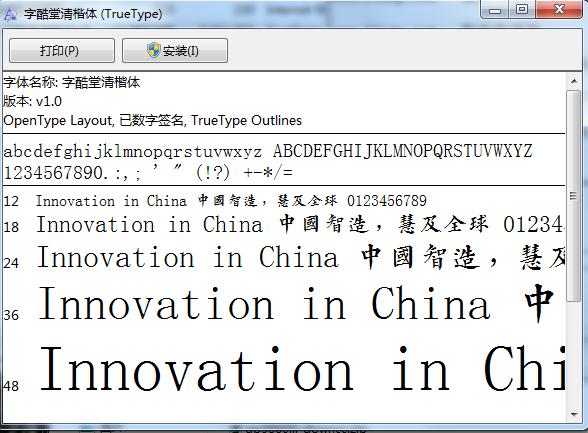
字酷堂清楷體是一款風(fēng)格獨(dú)特的字體,在設(shè)計(jì)領(lǐng)域有很多應(yīng)用,字體風(fēng)格是圓潤(rùn)厚重,書寫工整,廣告設(shè)計(jì)、平面設(shè)計(jì)、印刷包裝等都有用到,字酷堂清楷體字體支持winxp,win7,win2003,等大部份的電腦操作系統(tǒng),歡迎下載使用。
字酷堂清楷體古典書法味道很濃,適合用于古籍排版,包裝設(shè)計(jì)、書籍設(shè)計(jì)等方面。字酷堂清楷體字體是為繁體字庫(kù),簡(jiǎn)入繁出(輸入簡(jiǎn)體字直接顯示為繁體),基于中華人民共和國(guó)GB2312-80字符集標(biāo)準(zhǔn),共收入漢字9000余個(gè)。是一款非常不錯(cuò)的古風(fēng)字體。